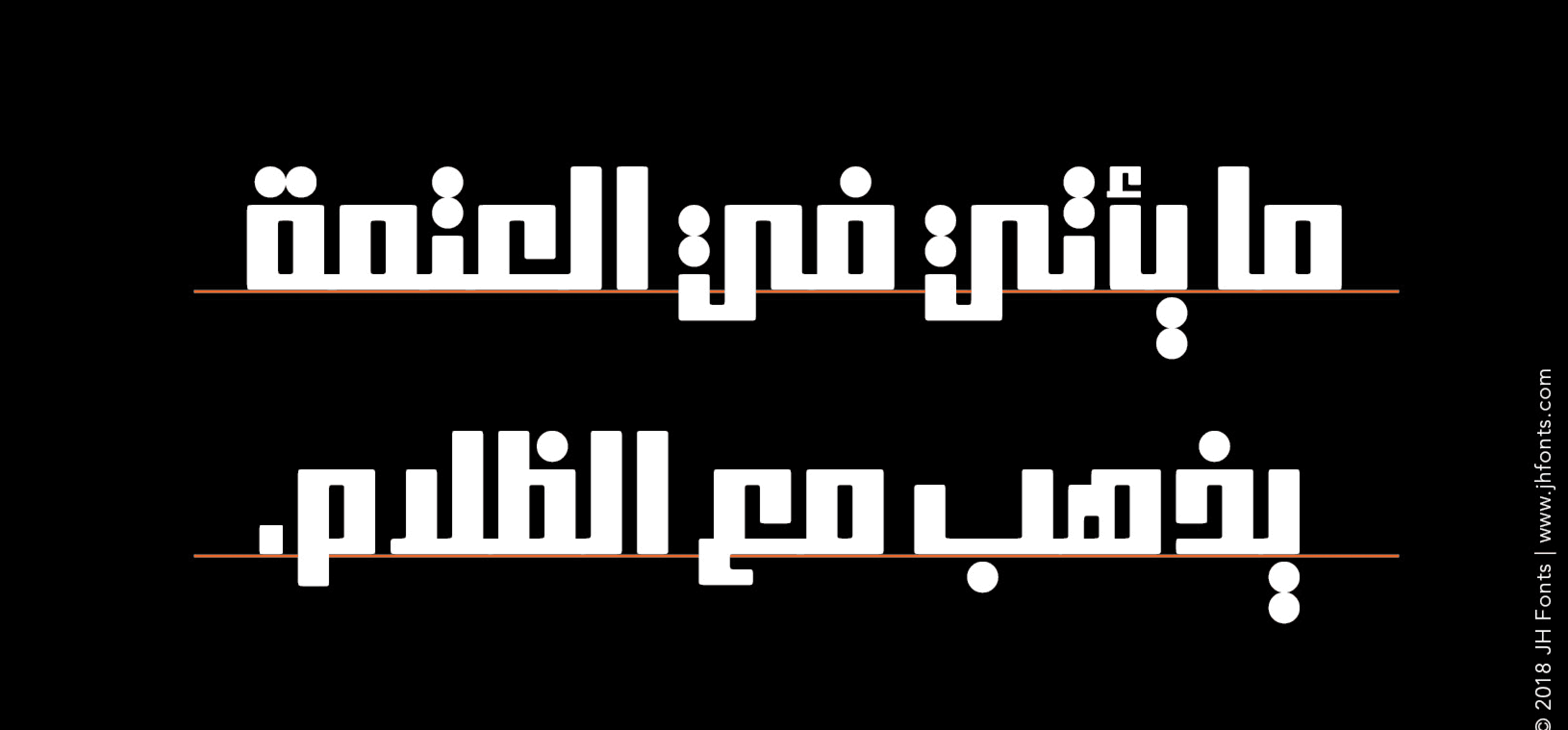
الخط "JH Fadi" هو خط عربي حديث من نوع كوفي مربع، ويتوفر بوزنين. يتميز بكونه مناسبًا للعناوين، وتصميم الشعارات، والعلامات التجارية، ولافتات الإعلانات. تم ضبط مواقع التشكيل بدقة وفقًا لمتطلبات الناشر.